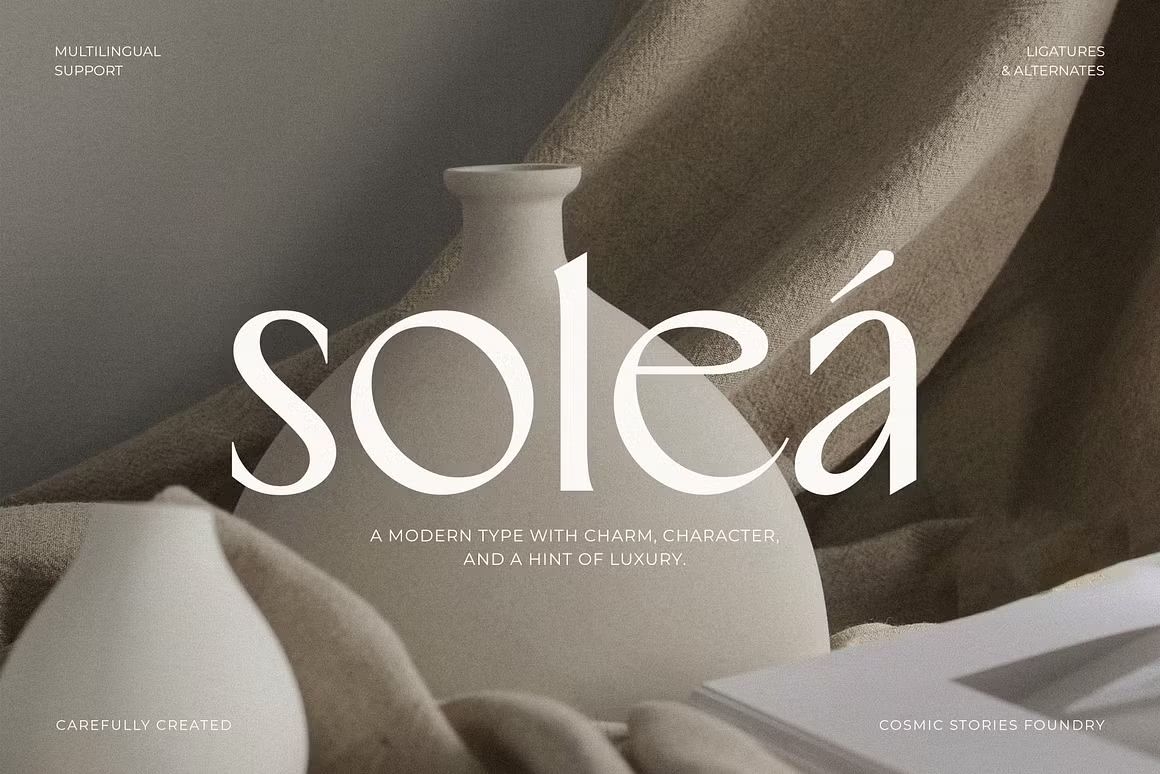
Soleá – Sophisticated & Modern Sans Font
Soleá adalah font sans serif yang modern dan elegan dengan sentuhan minimalis, ideal untuk branding, editorial, logo, dan desain visual yang membutuhkan tampilan bersih dan profesional.
Soleá adalah font sans serif yang menggabungkan kesan modern, bersih, dan elegan dalam setiap lekuk hurufnya. Didesain dengan proporsi seimbang dan garis tegas, font ini sempurna untuk proyek branding, editorial, desain fashion, logo, dan tampilan visual profesional lainnya. Soleá memberikan nuansa mewah dan sophisticated tanpa kehilangan keterbacaan.
• Gaya sans serif modern dengan sentuhan elegan
• Desain bersih dan minimalis untuk tampilan premium